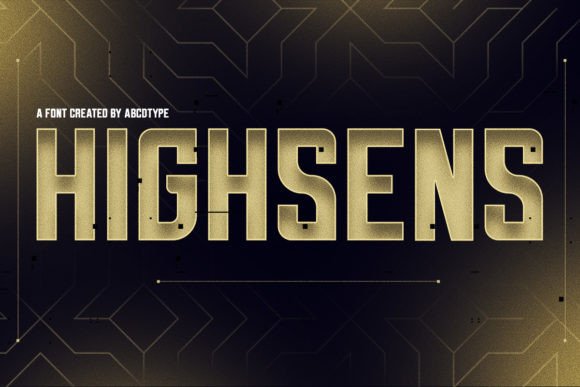
Highsens
หากคุณกำลังมองหาเนื้อหาคุณภาพสูงเช่น Highsens แพ็คเกจพรีเมียมนี้เป็นตัวเลือกที่ยอดเยี่ยมสำหรับโปรเจ็กต์สร้างสรรค์ของคุณ
ไม่ว่าคุณจะสร้างผลิตภัณฑ์ POD (Print on Demand) คำเชิญงานแต่งงาน หรือกราฟิกโซเชียลมีเดีย Highsens ก็เหมาะสมอย่างยิ่ง